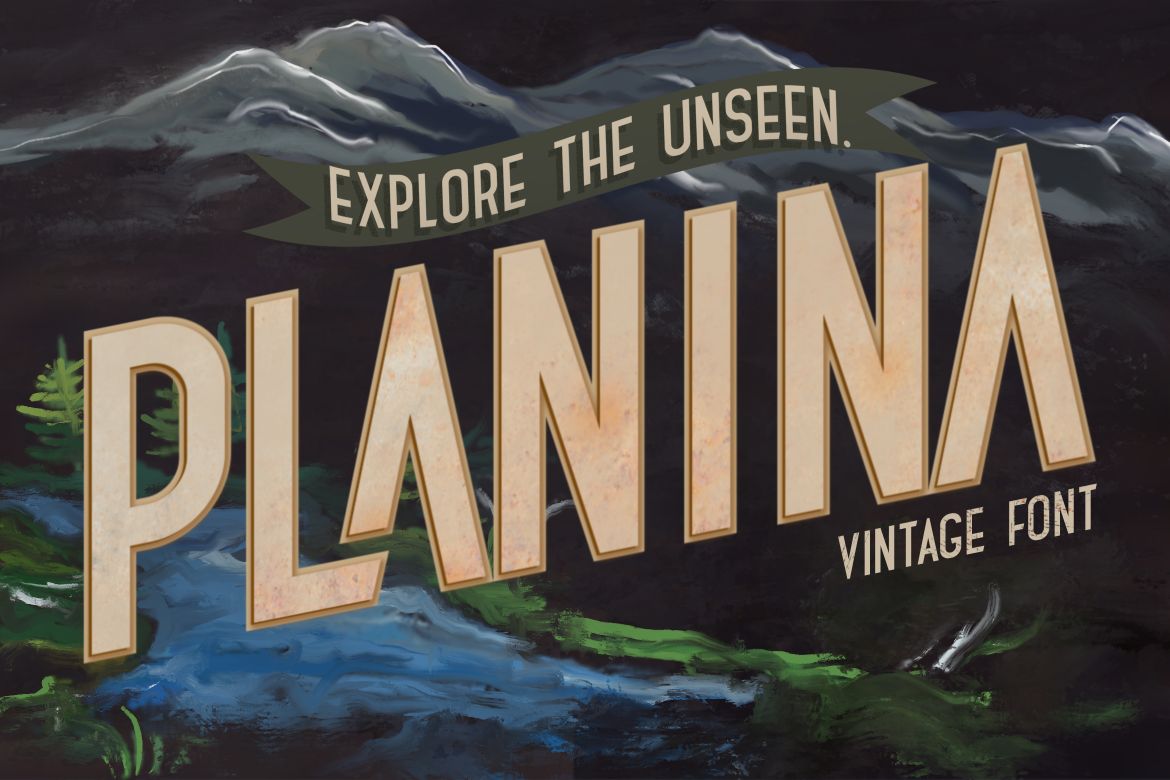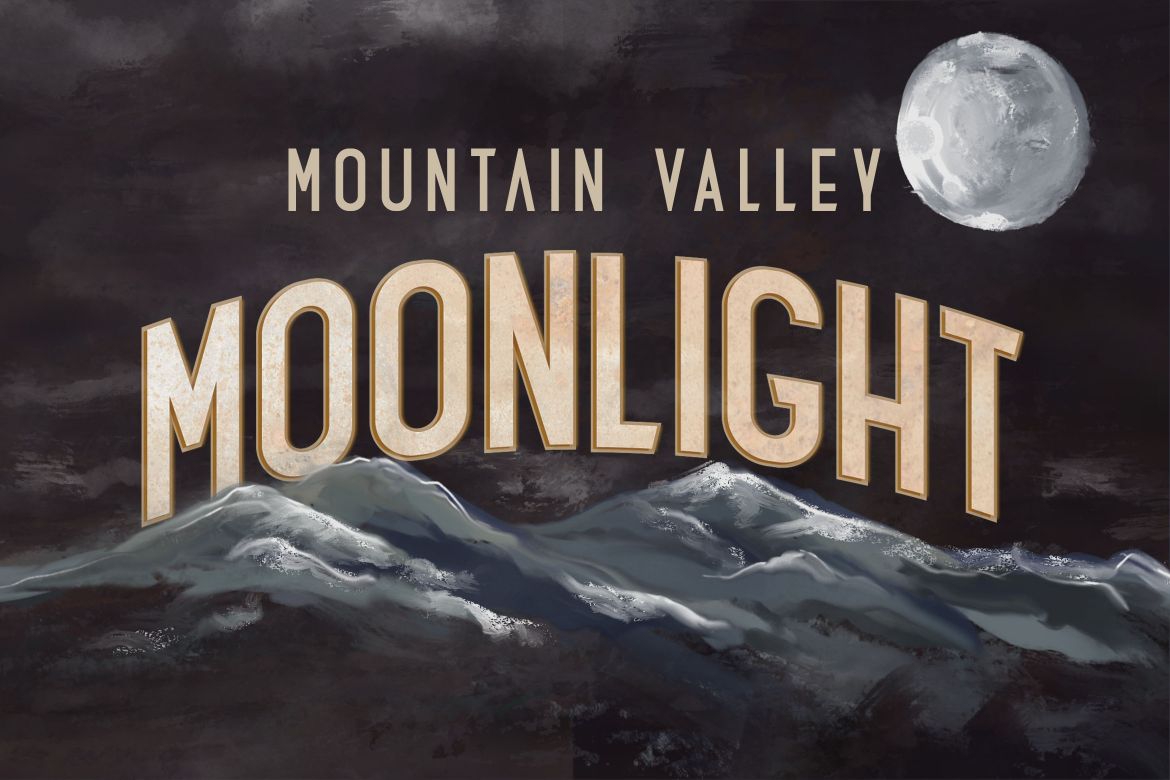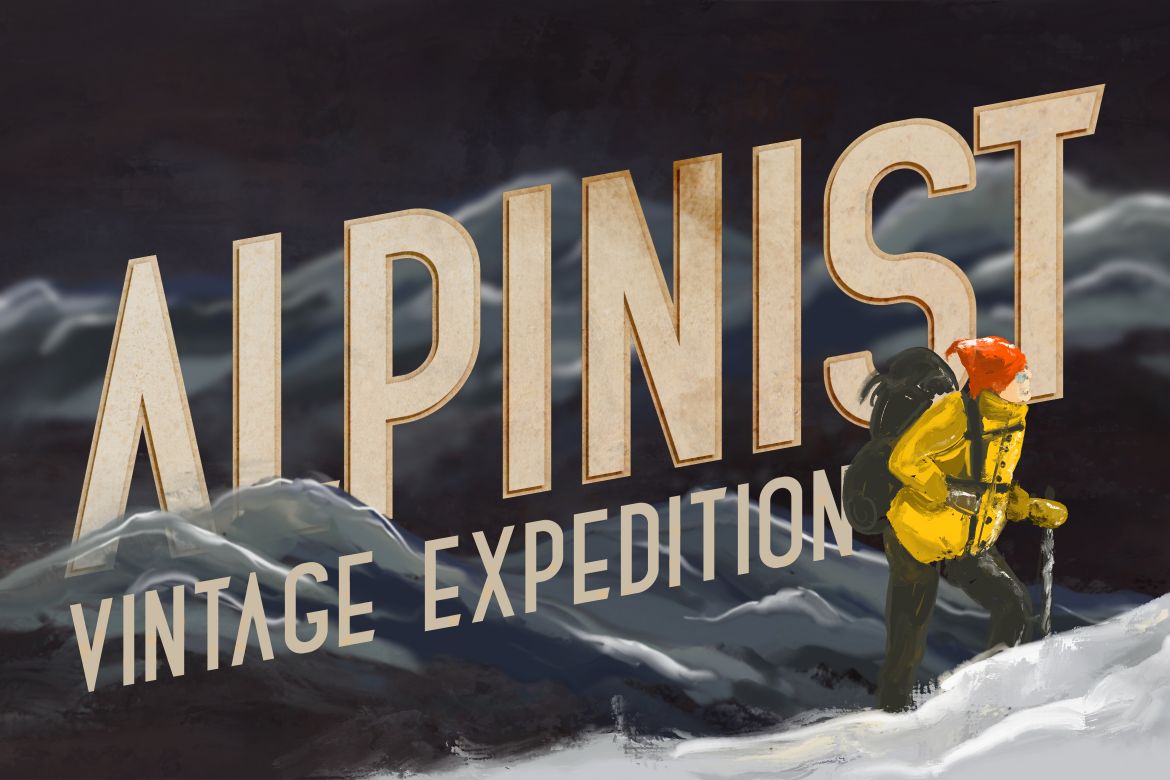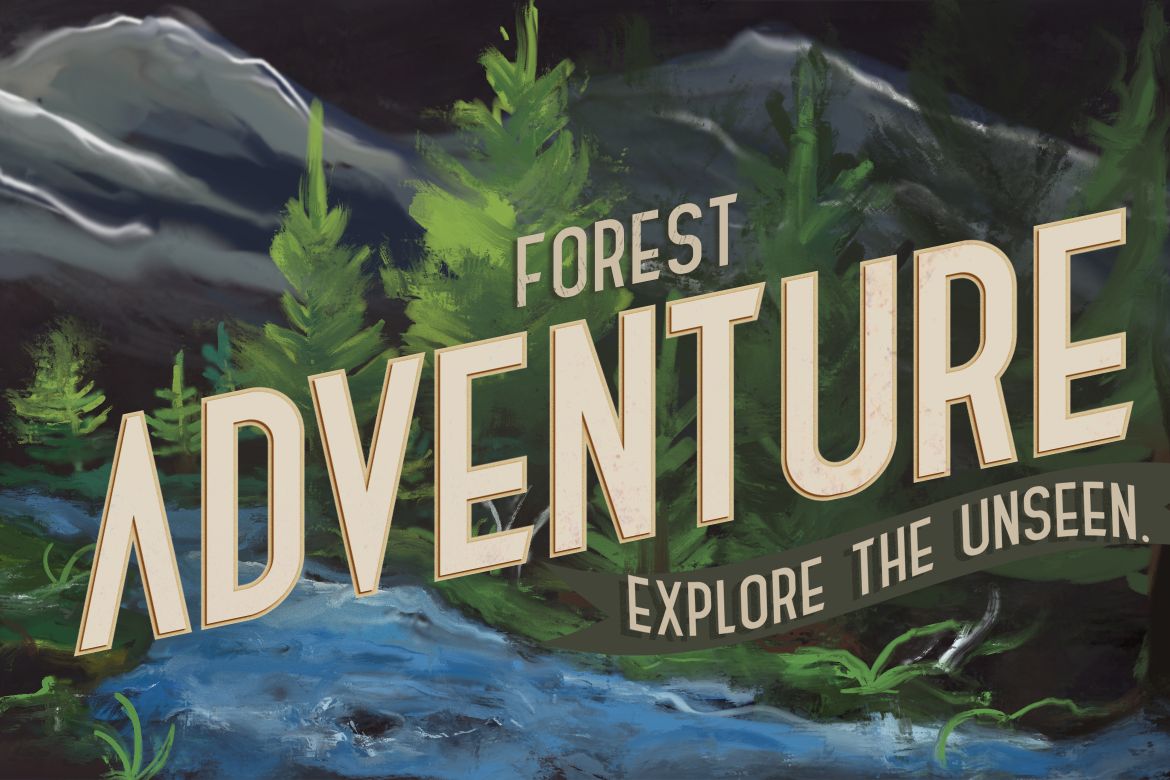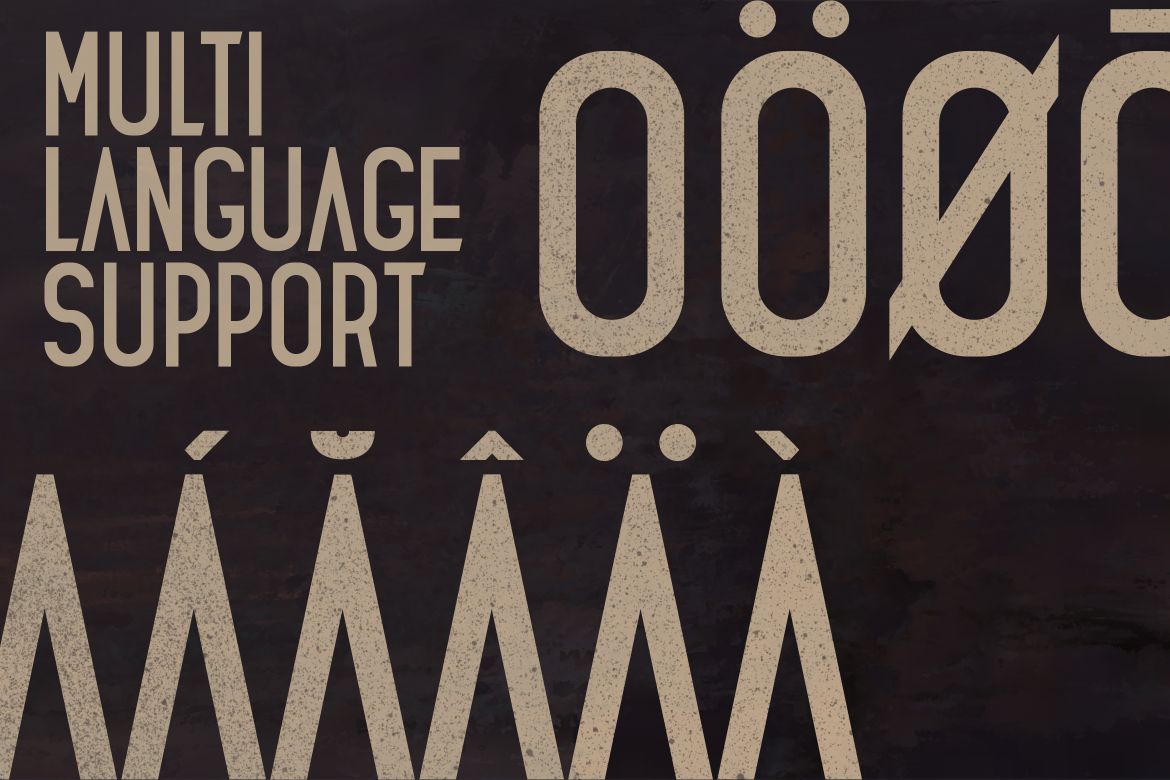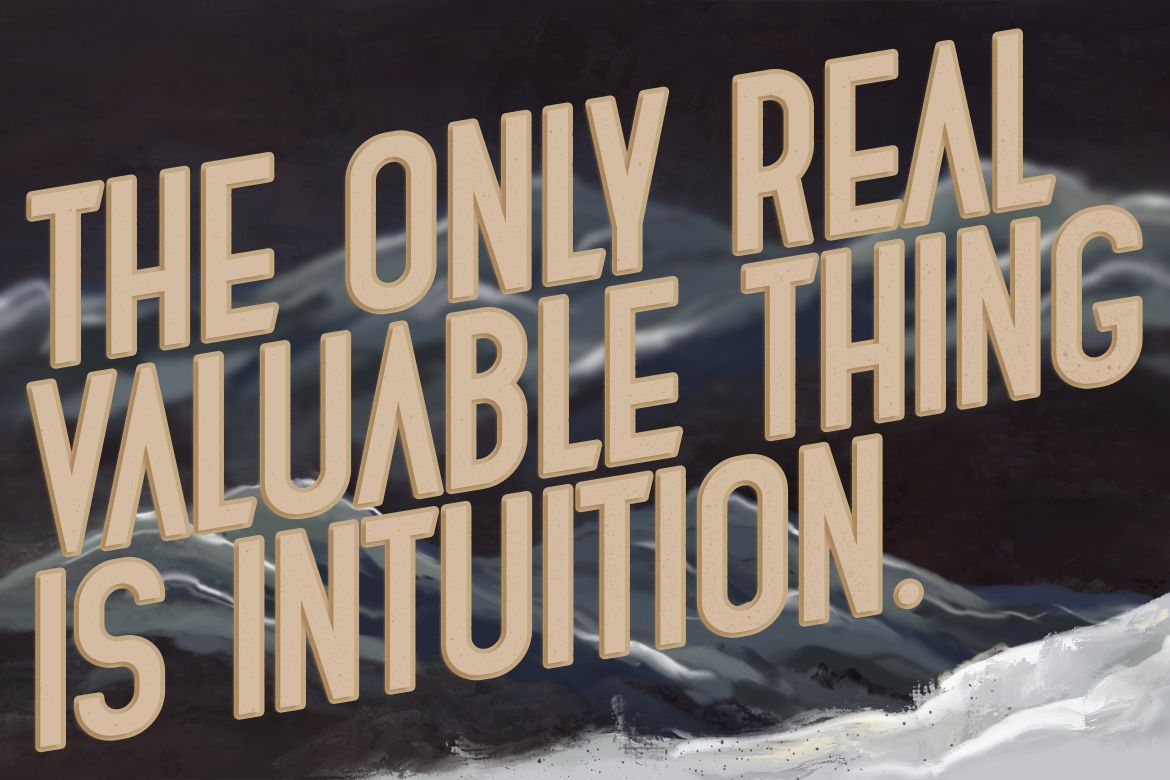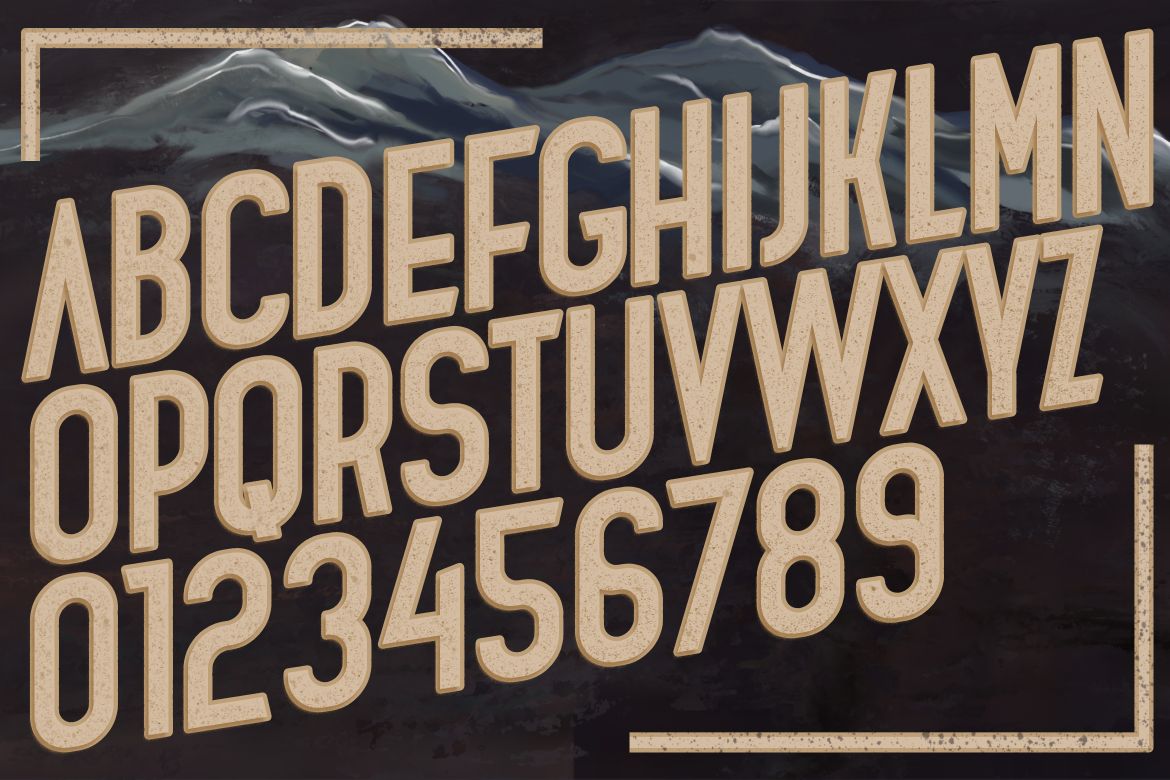
Fuente Planina
Con la fuente Planina, puedes transmitir tu mensaje fácilmente en tu diseño. Úsala para exhibiciones, etiquetas, ropa, escenas de cine, pósteres, títulos de películas, conciertos, portadas de álbumes, logotipos y mucho más.
Viene en 4 estilos: Regular, Cursiva, Contorno y Sello.
Inspirado en la tradición, la gente trabajadora y los años 1900, es ideal para proyectos retro y vintage, desde diseños claros hasta diseños de aspecto tosco.
La Planina se caracteriza por:
Alternativas estilísticas
Ligaduras
Caracteres internacionales (multilingües)
Puntuación y símbolos
Características de OpenType
Soporte multilingüe: inglés, albanés, danés, holandés, estonio, croata, bosnio, esloveno, finlandés, francés, alemán, islandés, italiano, noruego, portugués, español, sueco y muchos otros idiomas; consulte la lista completa de caracteres.